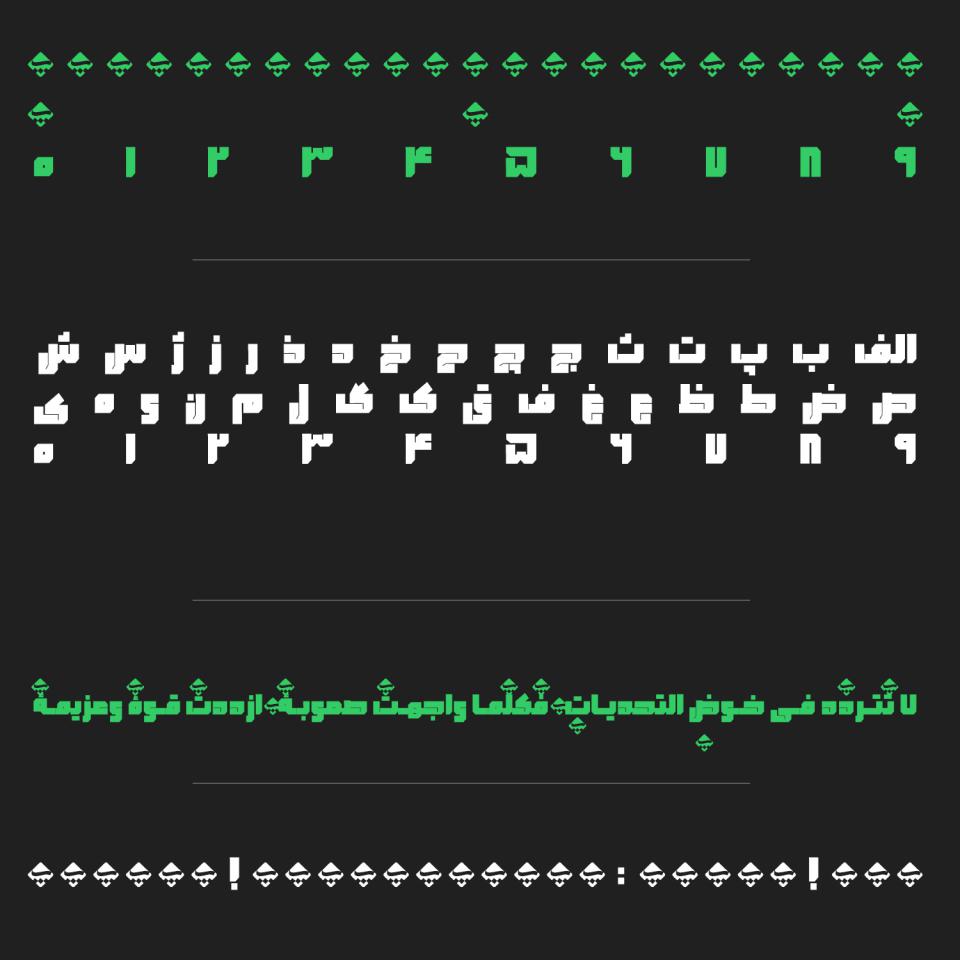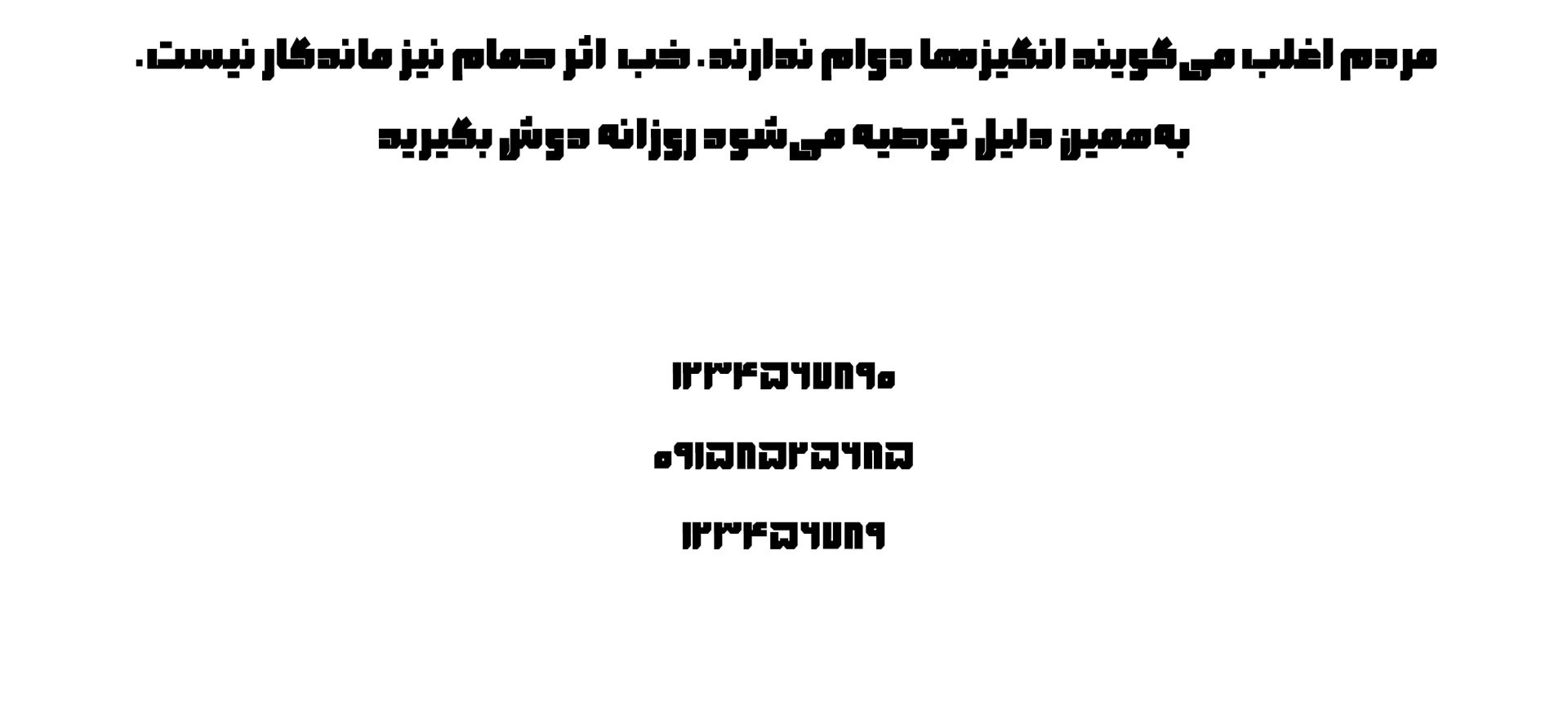
فونت گذرگاه فارسی Gozargah
فونت گذرگاه، یک انتخاب حرفه ای برای طراحانی است که به دنبال فونتی سنگین و قدرتمند برای پروژه های خود هستند. این فونت با وزن زیاد خود، به خوبی در عناوین، تیترها و پوسترهایی که نیاز به تأثیرگذاری بصری بالا دارند، خودنمایی می کند. گذرگاه فقط یک فونت ساده نیست؛ بلکه مجموعه ای کامل از حروف فارسی، عربی و اعداد فارسی را در خود جای داده و خیال شما را از بابت پشتیبانی از زبان های مختلف راحت می کند.
یکی از ویژگی های برجسته گذرگاه، طراحی خاص حروف آن است. چشم های ریز حروف، ظاهری مدرن و خوانا به متن می بخشند، در حالی که شکل منحصربه فرد حروف «واو» و «نون» به آن هویتی متمایز و جذاب داده است. این ویژگی ها باعث می شوند که متن شما نه تنها خوانا باشد، بلکه جلوه ای خاص و به یادماندنی نیز داشته باشد. البته باید به این نکته نیز اشاره کرد که سنگین بودن وزن این فونت، ممکن است در متون طولانی و بدنه متن، کمی خوانایی را کاهش دهد و بیشتر برای استفاده در عناوین و تیترها مناسب است.
گذرگاه در طیف وسیعی از پروژه ها کاربرد دارد. از طراحی جلد کتاب با موضوعات گوناگون گرفته تا خلق لوگوتایپ های منحصربه فرد و تایپوگرافی های چشم نواز، این فونت می تواند همراه شما باشد. در تبلیغات محیطی و بیلبوردها، جایی که اندازه و تأثیرگذاری متن اهمیت زیادی دارد، گذرگاه به خوبی خود را نشان می دهد. همچنین، در طراحی کارت ویزیت، تراکت، پوستر، کاورهای اینستاگرام و یوتیوب، طرح های چاپی و چلنیوم و بنرهای محیطی، این فونت می تواند به کار شما بیاید و به طرح های شما جلوه ای حرفه ای و مدرن ببخشد. با وجود اینکه این فونت رایگان نیست، ویژگی های خاص و کاربردهای متنوع آن، ارزش سرمایه گذاری را دارد و می تواند به پروژه های شما هویتی متمایز ببخشد.